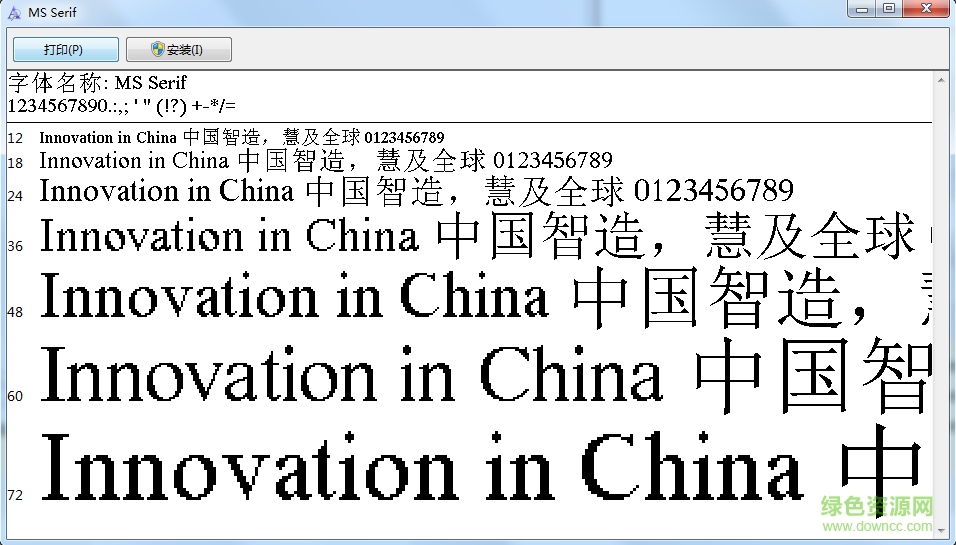
MS Serif英文字體
MS Serif是系統(tǒng)中的一款英文字體,常見于網(wǎng)頁WEB前端和瀏覽器中,便于用戶的英文書寫和閱讀,也是常用的網(wǎng)頁字體,需要的朋友歡迎來綠色資源網(wǎng)下載!
Serif字體介紹
Serif的意思是,在字的筆劃開始及結(jié)束的地方有額外的裝飾,而且筆劃的粗細(xì)會(huì)因直橫的不同而有不同。相反的,Sans Serif則沒有這些額外的裝飾,筆劃粗細(xì)大致差不多。
MS Serif字體
Serif和Sans Serif的一般比較:
1、Serif的字體容易辨認(rèn),因此易讀性較高。反之Sans Serif則較醒目,但在行文閱讀的情況下,Sans Serif容易造成字母辨認(rèn)的困擾,常會(huì)有來回重讀及上下行錯(cuò)亂的情形。
2、Serif強(qiáng)調(diào)了字母筆劃的開始及結(jié)束,因此較易前后連續(xù)性的辨識(shí)。
3、Serif強(qiáng)調(diào)一個(gè)word,而非單一的字母,反之Sans Serif則強(qiáng)調(diào)個(gè)別字母。
4、在小字體的場合,通常Sans Serif比Serif更清晰。